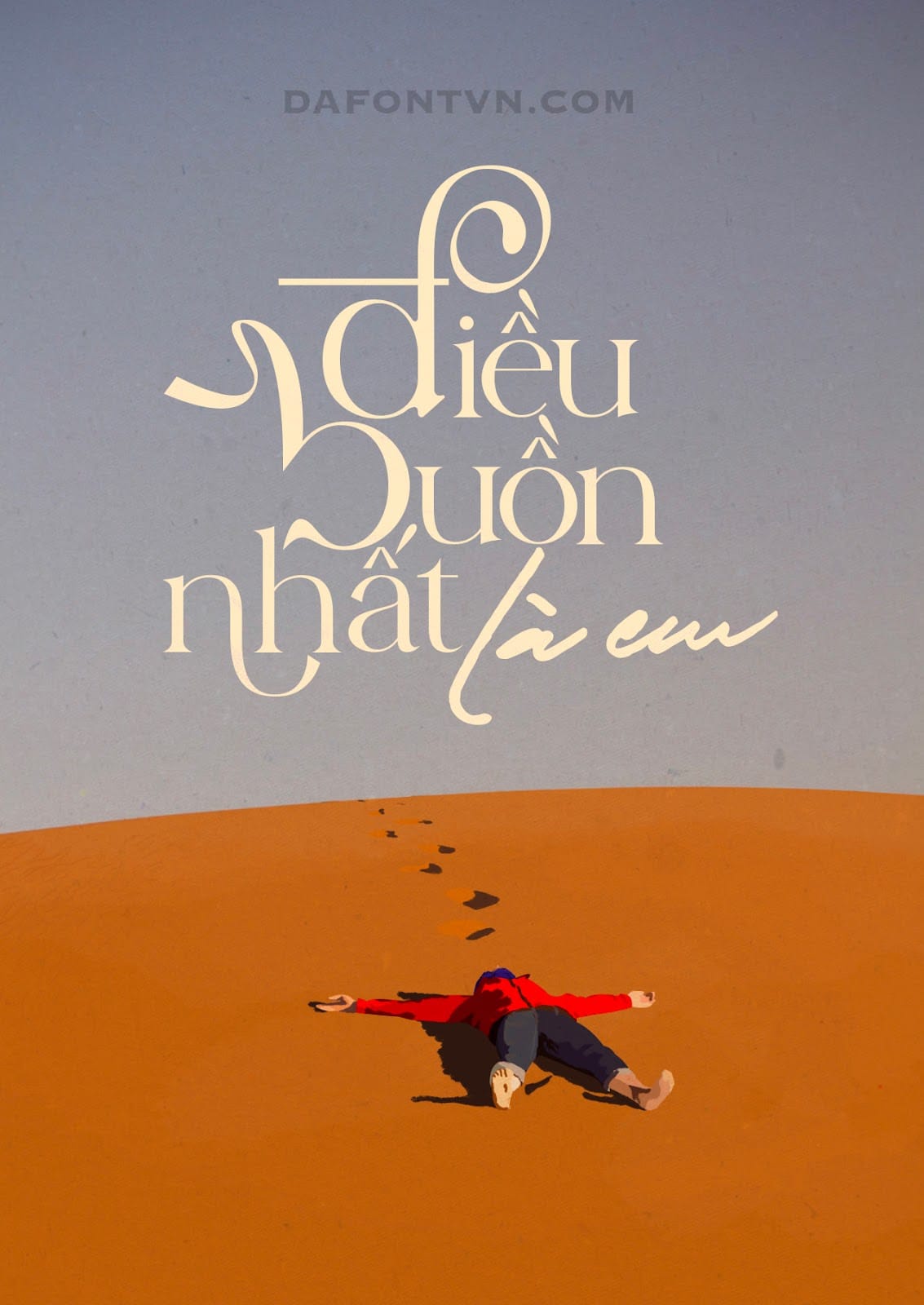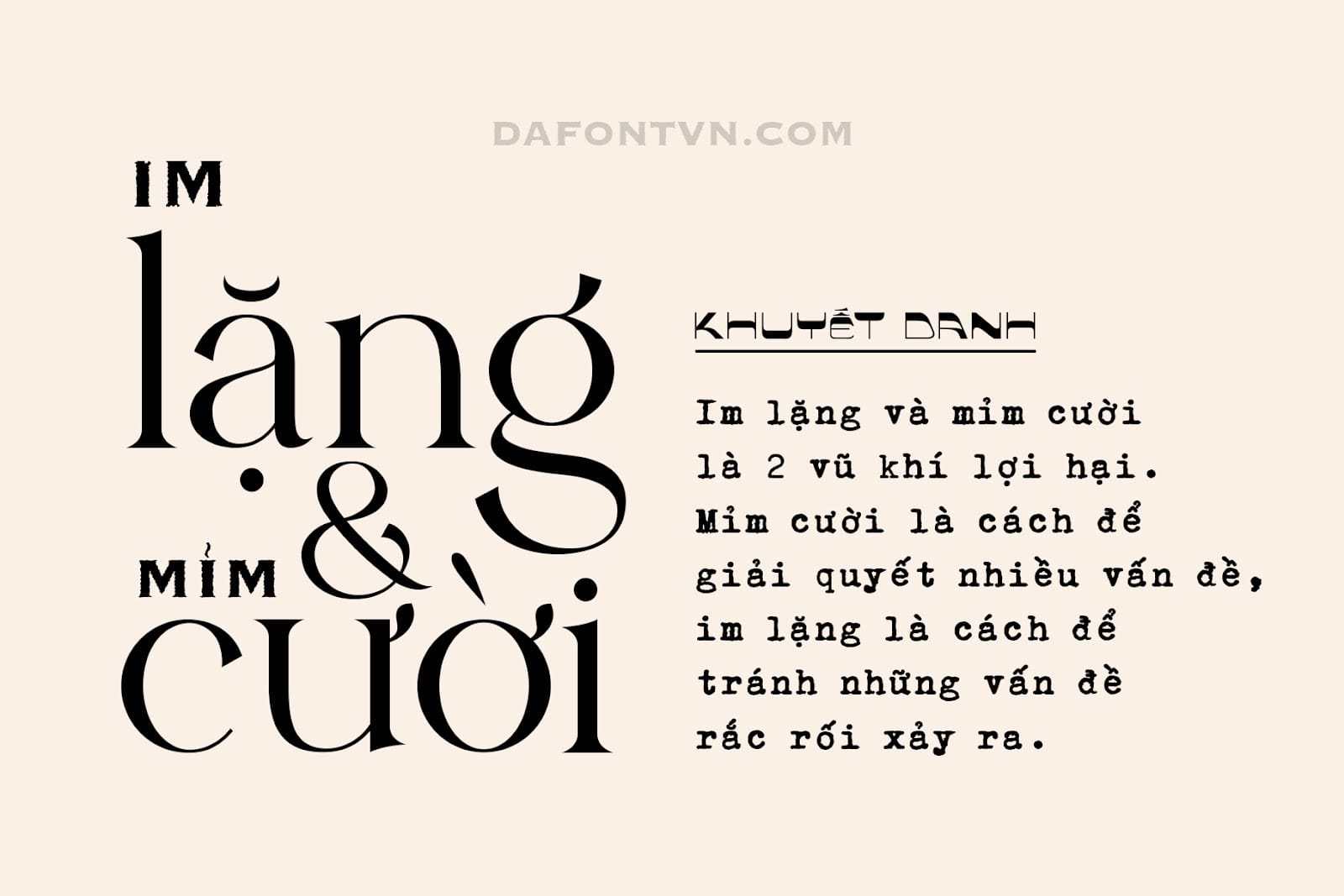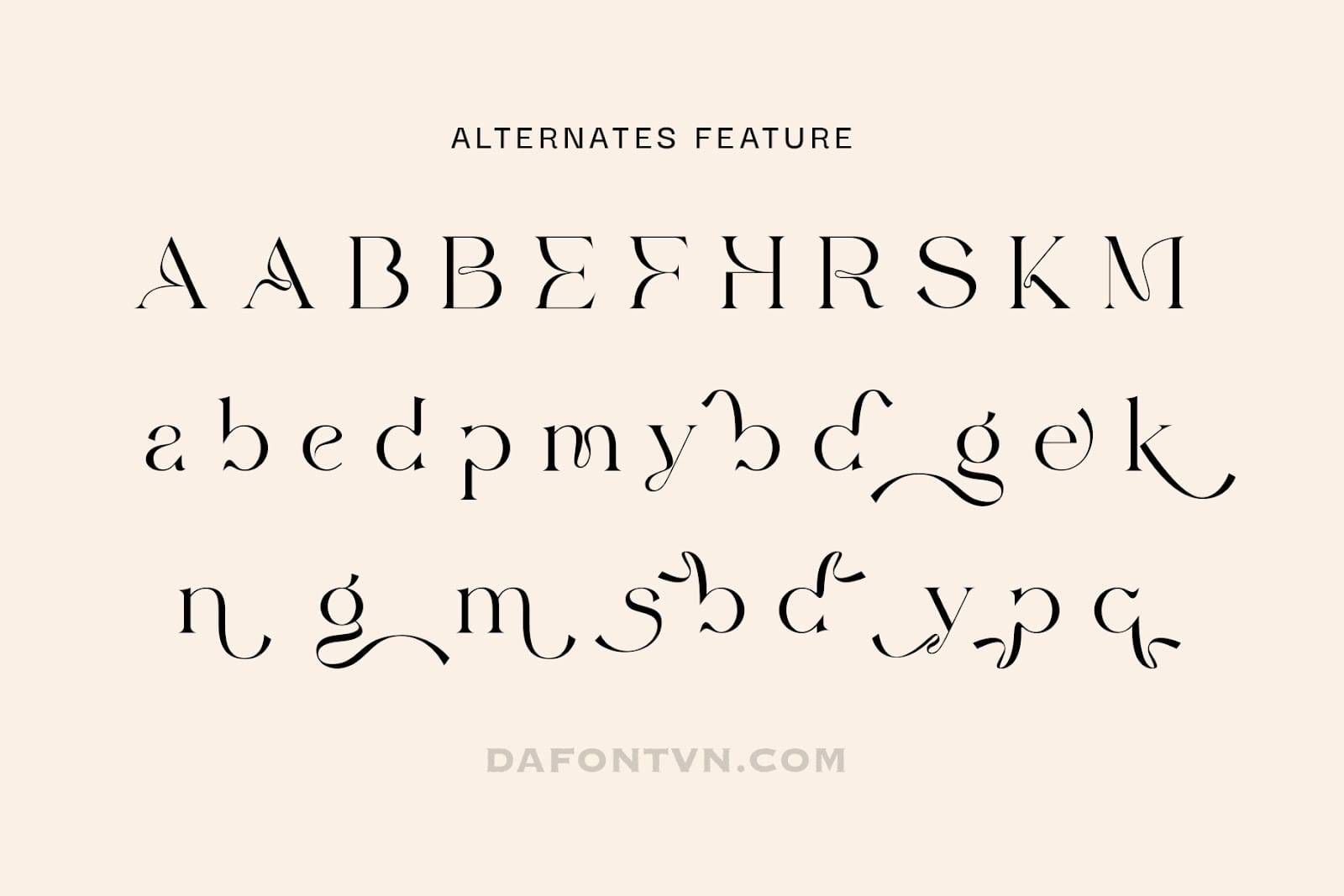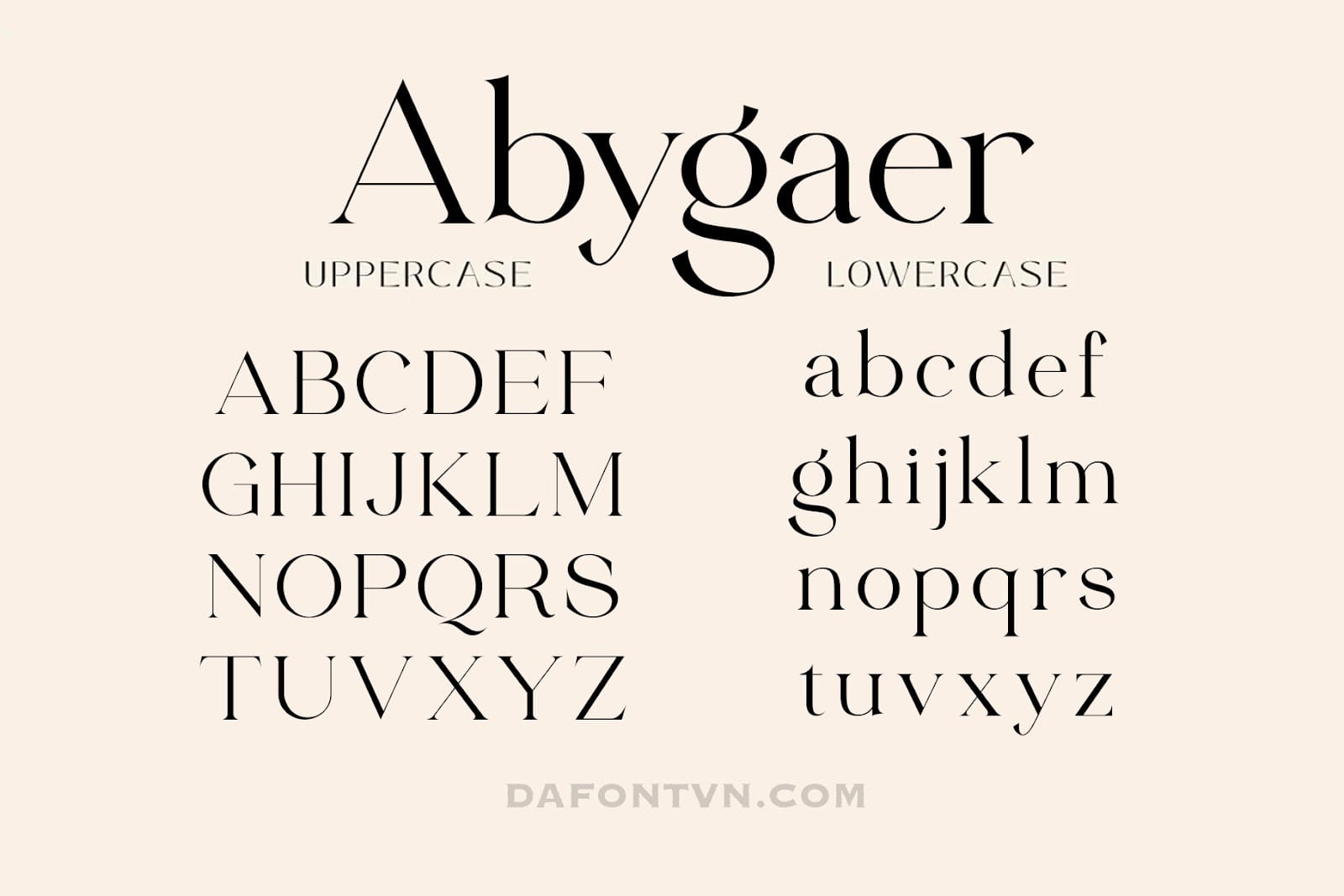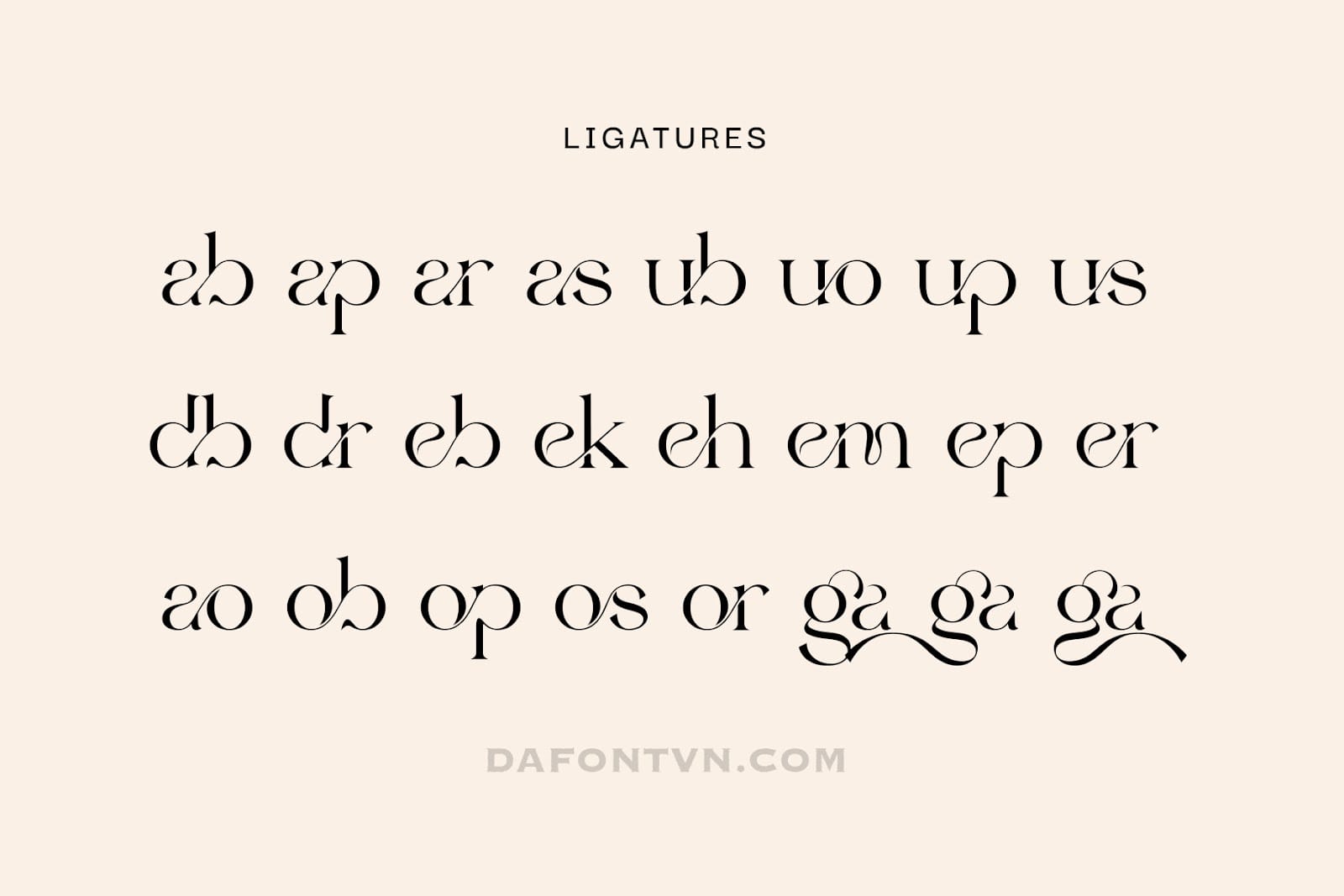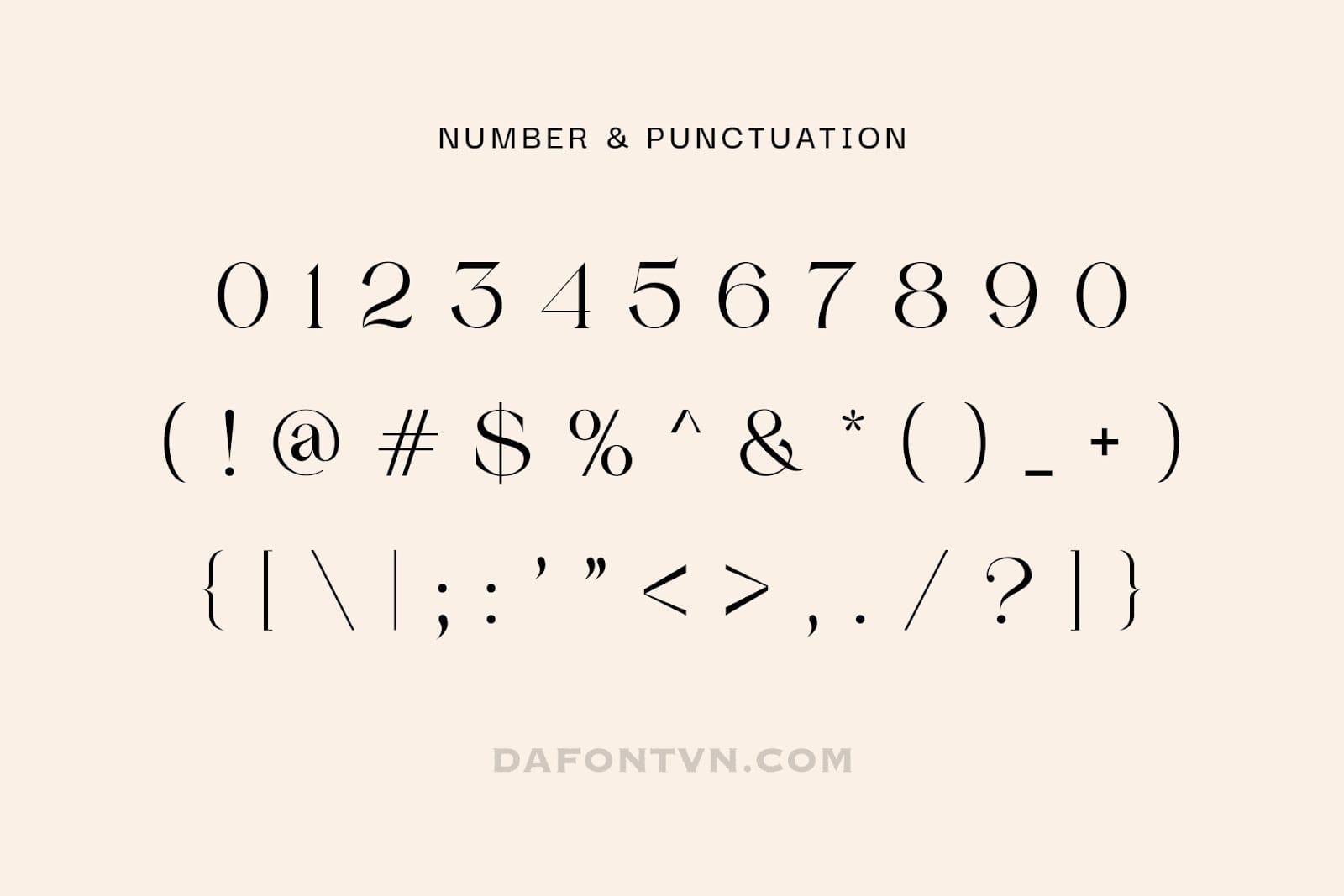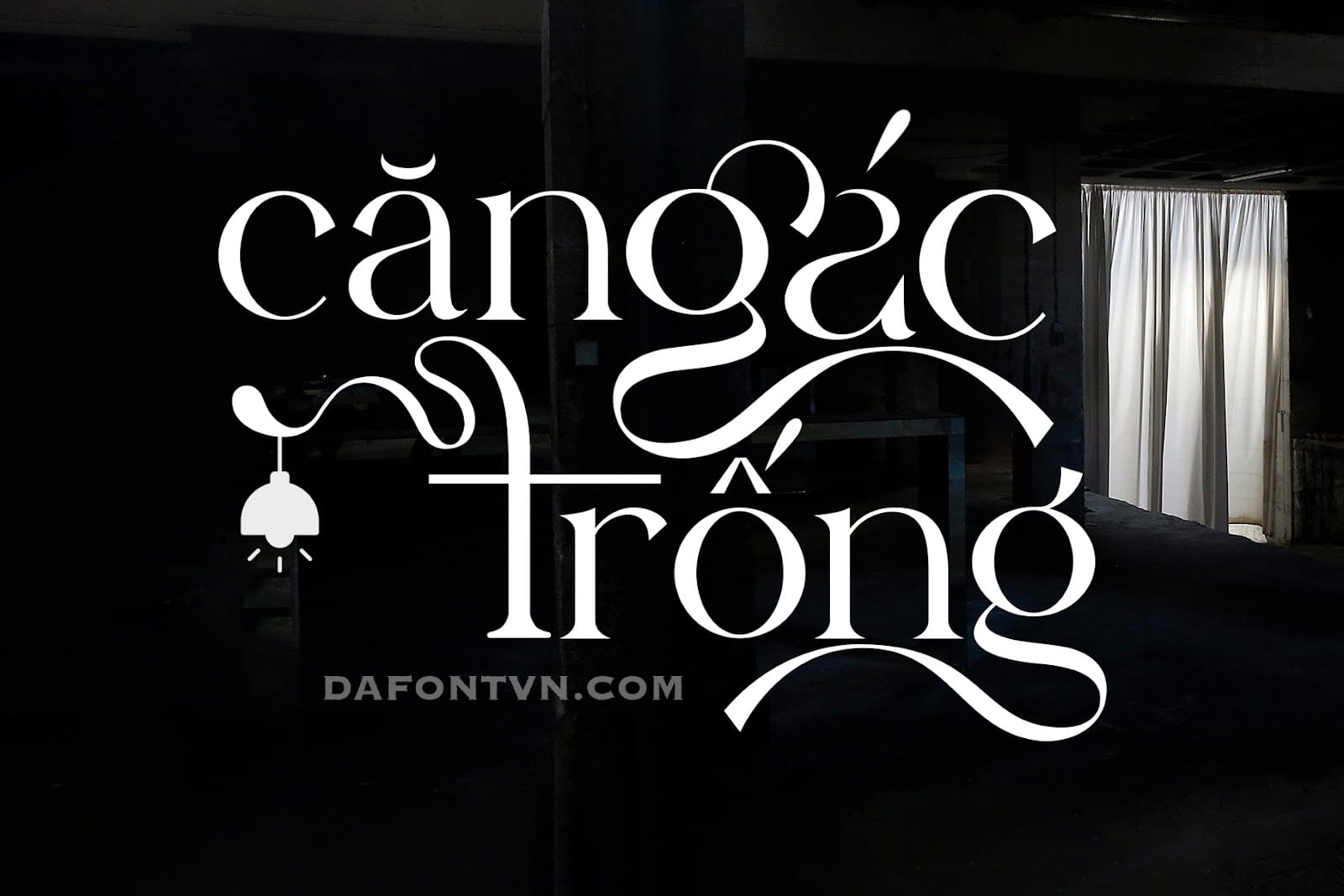
Font Abygaer là một kiểu serif hiện đại với OpenType đầy phong cách với kiểu chữ uốn lượn hài hòa với nhau để tạo thành các kiểu chữ độc đáo và sang trọng.
Một số lượng lớn các chữ ghép OpenType đan xen và xen kẽ, có nghĩa là bạn có nhiều lựa chọn và sự đa dạng trong việc thiết kế của mình. Phông chữ phù hợp cho nhiều thiết kế khác nhau như tiêu đề, bìa sách, tạp chí, xây dựng thương hiệu, thiết kế typography…
Font Abygaer việt hóa đầy đủ, kerning, chỉnh sửa lại và tối ưu hóa cũng như được mã hóa PUA.